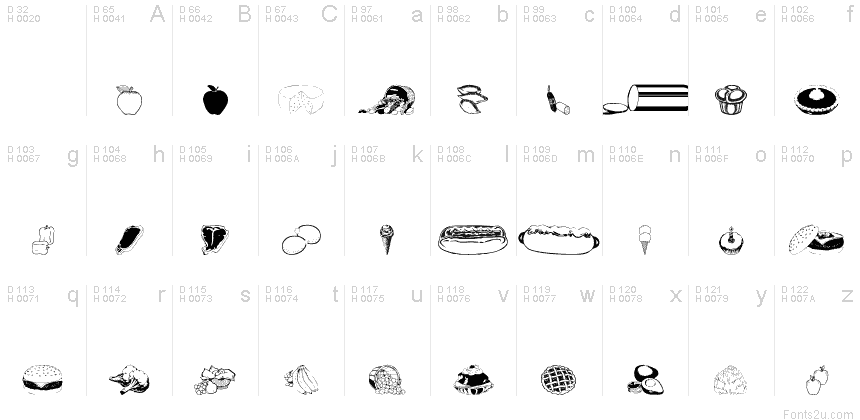
WM Food 2 je bezplatný font typu dingbats složený z ručně kreslených ikon pečiva a drobného občerstvení. Celá sada sází na domáckou pohodu – najdete v ní krusty koláčů, zdobené cupcaky i poctivého hot doga. To vše vykreslené výraznými, lehce hrubými linkami, které připomínají spíše ilustrace z menu než sterilní grafiku.
Skvěle se hodí na jídelní lístky, letáky na pekařské bazary, plakáty do kaváren, kartičky s recepty nebo pozvánky na večírky, kde bezplatný font s jasnými motivy jídla rychle upoutá pozornost. Kresby jsou jednoduché, ale živé, takže skvěle poslouží i na štítky do scrapbooků, nálepky na obaly nebo hravé nadpisy, které potřebují přátelský, ručně vyrobený nádech.